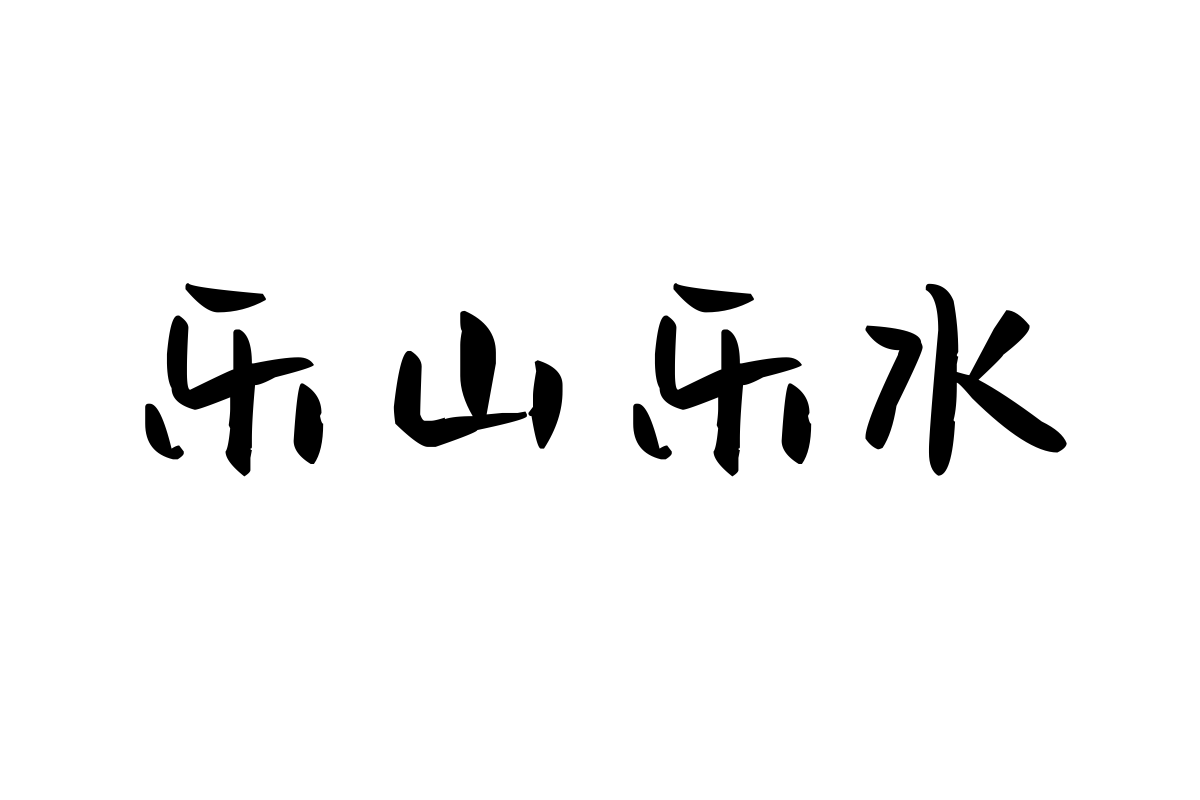
蝉羽丘陵颖宝 是汉仪字库中的一款字体,具有独特的设计风格和特点。该字体采用了现代简约的线条和形状,使得整体看起来简洁而富有层次感。同时,蝉羽丘陵颖宝 也注重细节的处理,每个笔画都经过精心打磨,使得整体字形更加流畅自然。此外,该字体还具有一定的艺术感,适合用于各种需要展示个性和创意的场合。总的来说,蝉羽丘陵颖宝 是一款非常优秀的字体,值得一试。